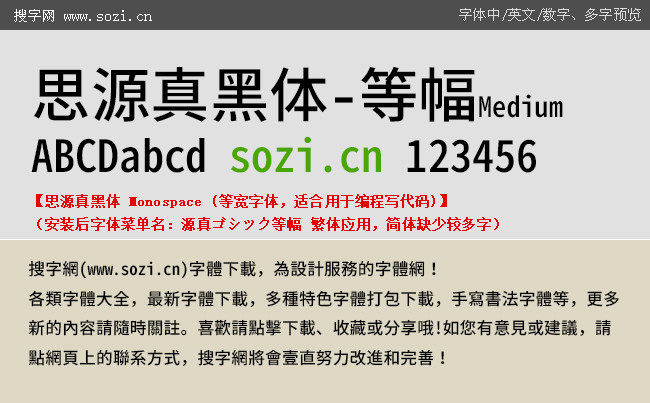
思源真黑體-等幅Medium
搜字網(wǎng)給大家提供一款思源真黑體-等幅Medium中文字體下載,思源真黑體字體是源于Google的開源字體思源黑體,保留了思源黑體原版的優(yōu)雅以及高可讀性的特色,并在思源黑體的基礎(chǔ)上做出了變化,使得整套字體看起來更加銳利清晰。等寬字體 GenJyuuGothic - Monospace適合用于編程寫代碼。